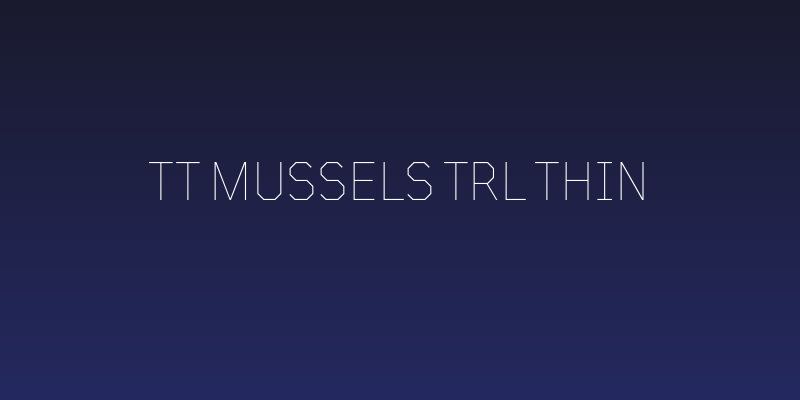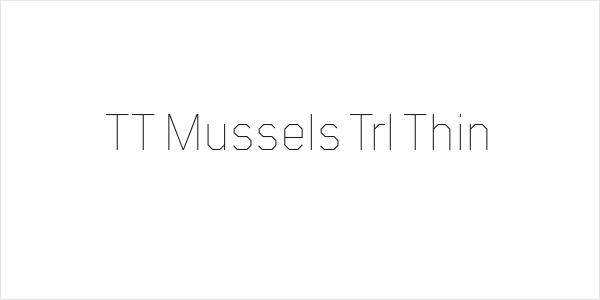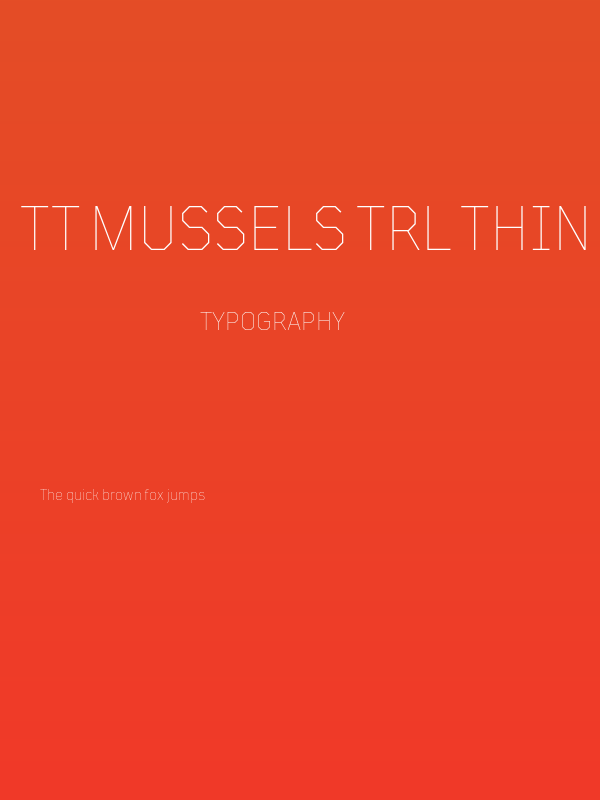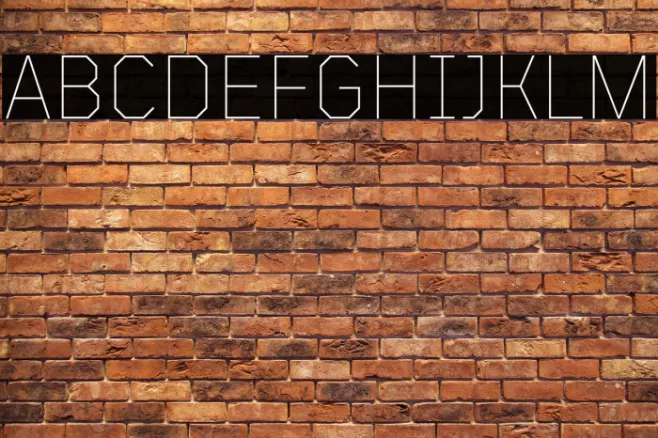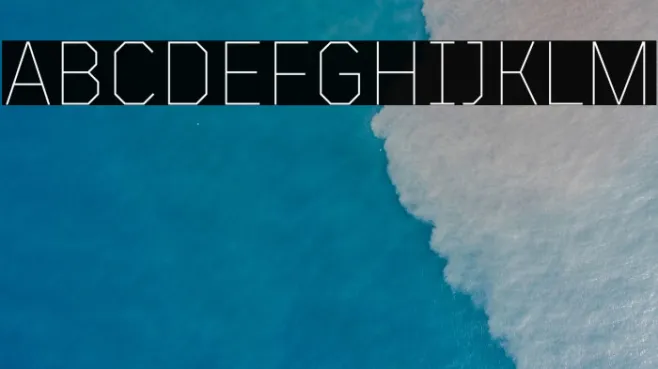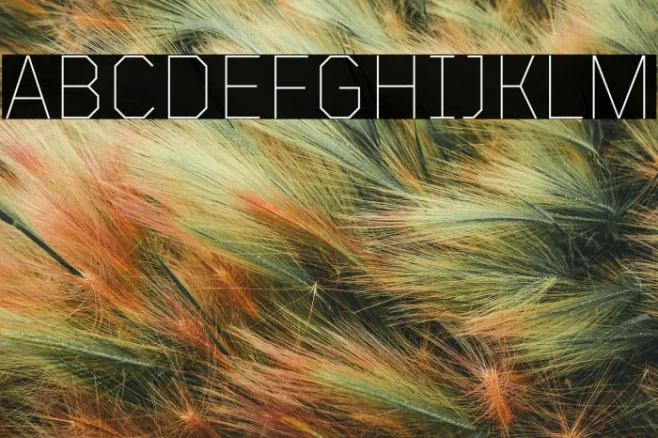
TT Mussels Trl Thin Font
✎ Futuristic
| Anwendungsfall | Logos, Headlines, Digital Interfaces |
| Vorgeschlagene Projekte | Ideal for tech branding, modern posters, digital interfaces, and minimalist graphic design projects. |